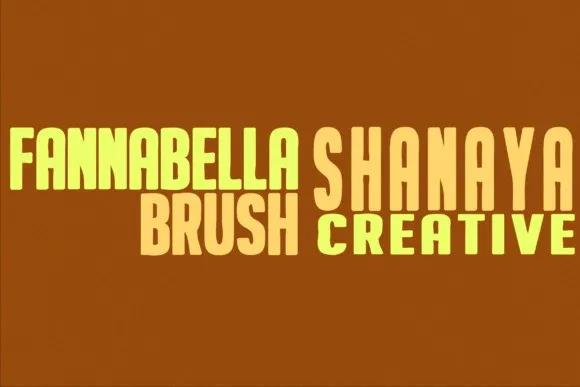
Fannabella Display Font – Download Grátis
Agora está disponível uma nova opção para a sua coleção de fonts: Fannabella Display Font, criada pelo talentoso designer Shanaya Creative. Este moderno e minimalista tipo de texto foi projetado especificamente para ambientes de luxo, moda e design estiloso, oferecendo um enfoque único que torna-o perfeito para headlines, logotipos e uso em displays. Com sua aparência cuidadosamente planejada, Fannabella Display Font traz uma sensação de rusticidade e descontração à qualquer projeto, sem precisar recorrer a imagens clip art. Suas linhas grossas e estilo de caneta criam um detalhamento profundo e rico que se torna ideal para destacar ideias inovadoras em qualquer projeto. Esta font é perfeita para criar designs rústicos e contemporâneos, mantendo uma aparência minimalista enquanto transmite o valor e a sofisticação necessários para estilos de marca ou design. Fannabella Display Font se destaca como uma escolha ideal para aqueles buscando adicionar um toque único ao seu trabalho visual. Seja você um designer gráfico, editor de texto ou apenas alguém que aprecia a beleza da boa fonte, Fannabella Display Font pode ser o que está procurando. Seu formato robusto e moderno é uma ótima opção para destacar seus trabalhos, torná-los mais interessantes e garantir um impacto duradouro em qualquer projeto visual.